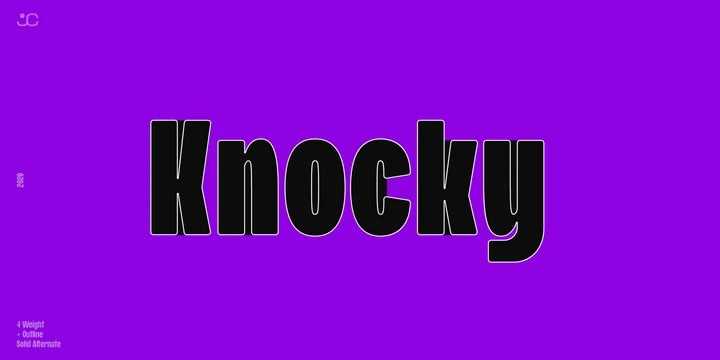
A Knooky Font é uma tipografia que combina modernidade e nostalgia num só, formando um design único e divertido. Seu estilo elegante oferece uma aparência clara e contemporânea, perfeitamente adaptada para ambientes digitais e gráficos de diferentes formatos. Além dos caracteres normais, número e símbolos, Knooky traz alternativas sólidas que não apenas substituem esses elementos, mas também adiciona um toque de elegância ao design. O estilo em relevo acentua ainda mais o aspecto único desta fonte, tornando-a uma escolha irresistível para qualquer projeto gráfico. Ideal tanto para uso no dia a dia quanto para estilos arrojados e inovadores, Knooky é perfeito para adicionar um toque especial a qualquer design.